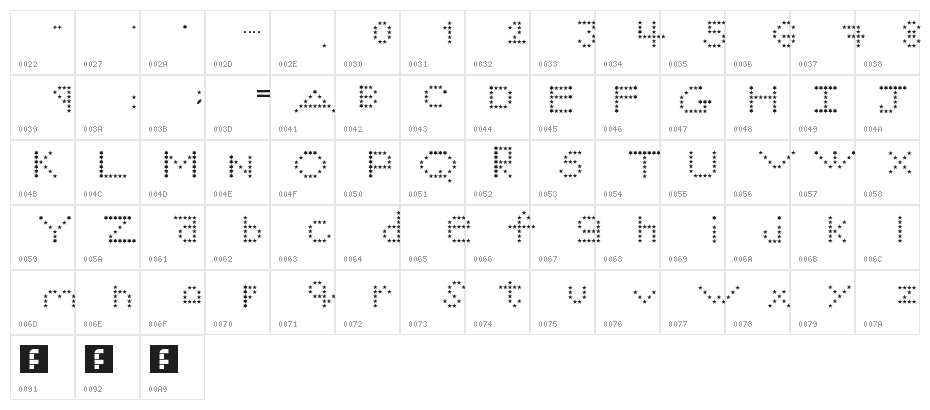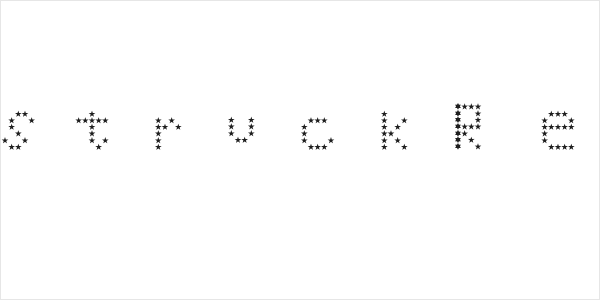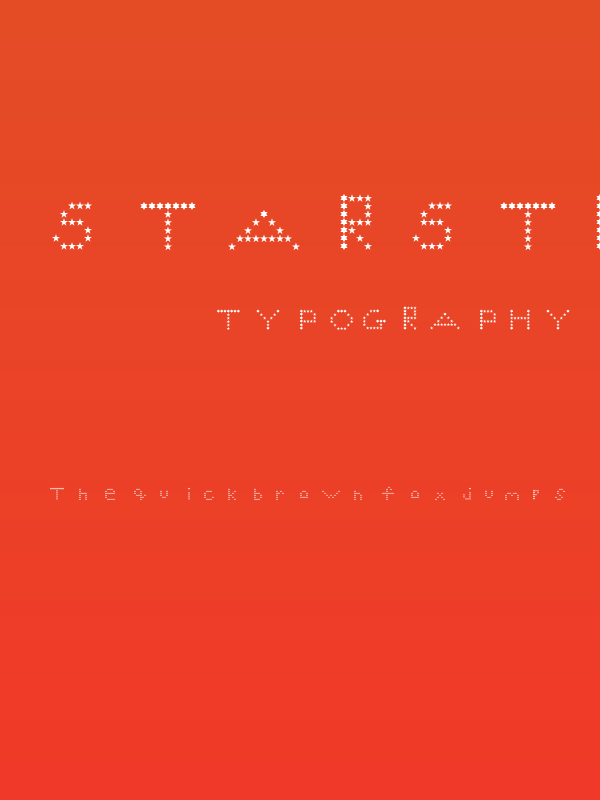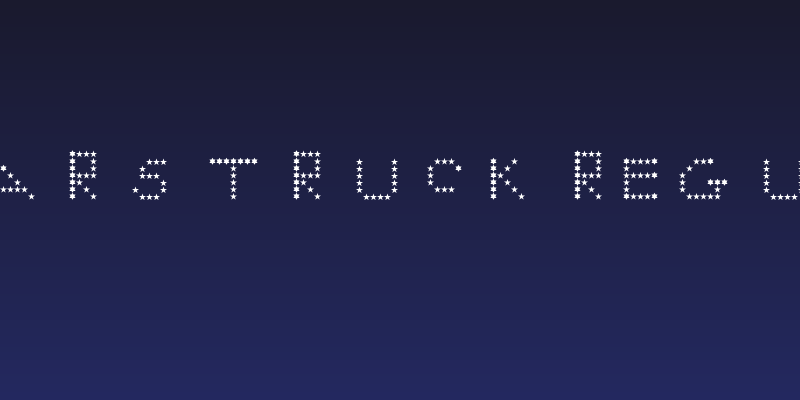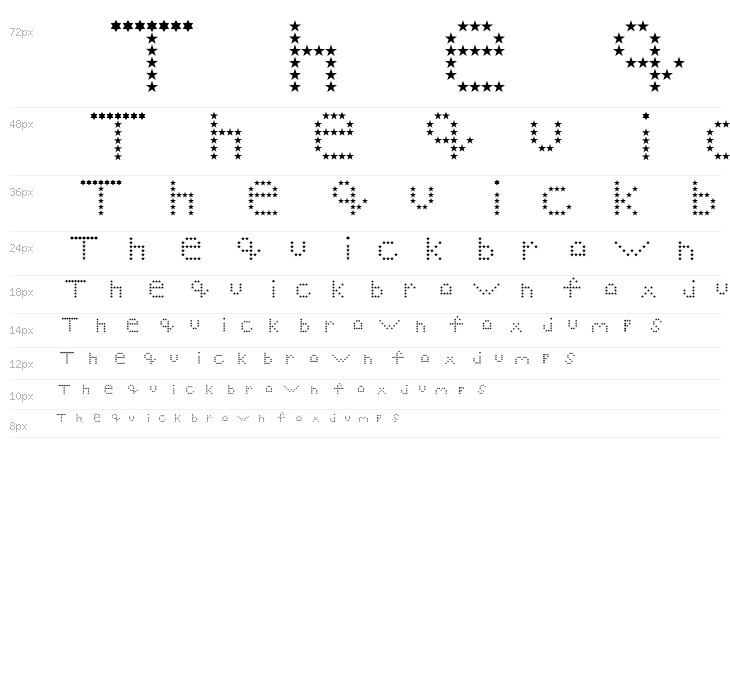
Starstruck Regular Font
| Gesamtstil | Playful and whimsical |
| Anwendungsfall | Headlines, Logos, Decorative text |
| Vorgeschlagene Projekte | Children's books, party invitations, creative branding, posters, and decorative projects. |